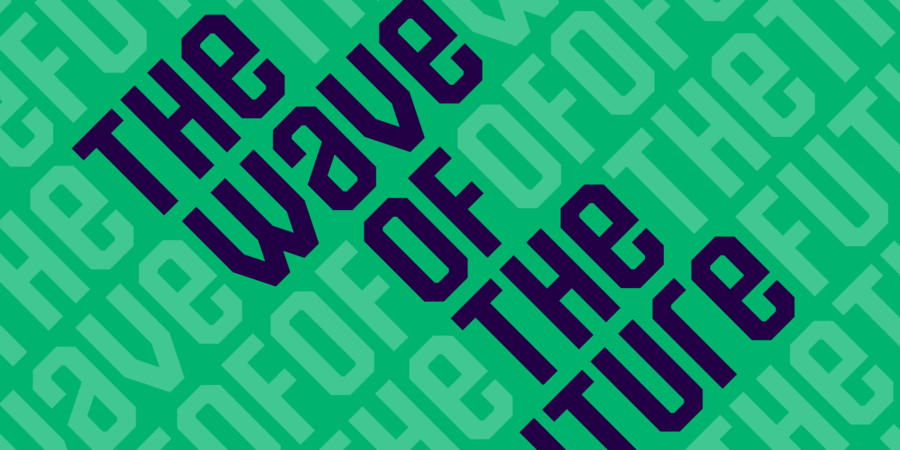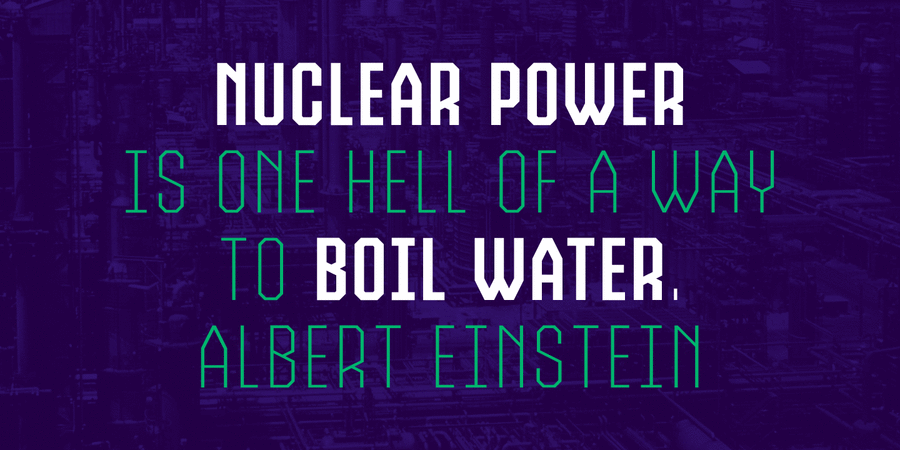
Fisionada – це стиснутий шрифт без засічок із гострими краями і дуже технічним виглядом. Вузькі пропорції роблять його дуже ефективним для економії простору, а геометричні характеристики роблять привабливим вибором для використання в акциденції, наприклад, футуристичні логотипи, відеоігри, науково-фантастичний контент. Шрифт найбільш придатний для заголовків і коротких текстових блоків. Fisionada складається з 8 накреслень, кожен з яких містить капітель і набір гліфів для кількох мов. Шрифт розробив Пабло Балселлс у 2023 році.
Асоціації з сімейством шрифтів FisionadaОсобистість і характер гарнітури:
комп'ютерний, електронний, рівний, точний, логічний, холодний, автоматичний, техногенний, твердий, статичний, різкий, чіткий, стійкий, стабільний, прямокутний, міський, сучасний, машинний, інженерний, урбаністичний, креслярський, сталевий, індустріальний, залізний, промисловий, футуристичний, ламаний, незграбний, помітний, кінематографічний, ритмічний, гучний, високий, стрункий, гострий, худий, монотонний, тісний, стиснений, вібруючий, смугастий, ігровий, тонкий, легкий, скляний, крихкий, дротяний, гранчастий, мужній, надійний, впевнений, переконливий, серйозний, сильний, військовий, армійський, байдужий, рубаний, яскравий, активний, робочий, оригінальний, спортивний, важкий, потужний, грізний, суворий, авторитетний, значний, грубий, кондовий, сміливий, важливий, монументальний, крутий, амбітний, брутальний, жорсткий, чорний, тоталітарний, політичний, революційний, щільний, солдатський, мотивуючий, кричущий
комп'ютер, конструктор, креслення, інженер, автоматика, урбаністика, електроніка, авто, інструмент, робот, гра, техніка, прилад, автомат, технології, залізо, фантастика, кіно, лего, іграшка, кубики, хмарочос, кінотеатр, архітектура, комп'ютерна гра, дизайн, Місто, гаджет, промисловість, війна, армія, зброя, завод, металургія, верстат, тара, склад, порт, ящик, патрони, ремонт, депо, шолом, уніформа, вагон, шутер, екшен, страйкбол, взуття, айтішник, IT, айті, астрономія, спорт, машинобудування, охорона, захист, паливо, будівництво, цегла, робочий, кіберспорт, електростанція, танк, вантажівка, тренажери, екскаватор, позашляховик, блокбастер, бойовик, далекобійник, реп, концерт, супергерой, шахта, будматеріали, енергетика, революція, шахтар, мотор, двигун, Футбол, страйк, Протест, сталевар Гарнітура має ознаки стилів: